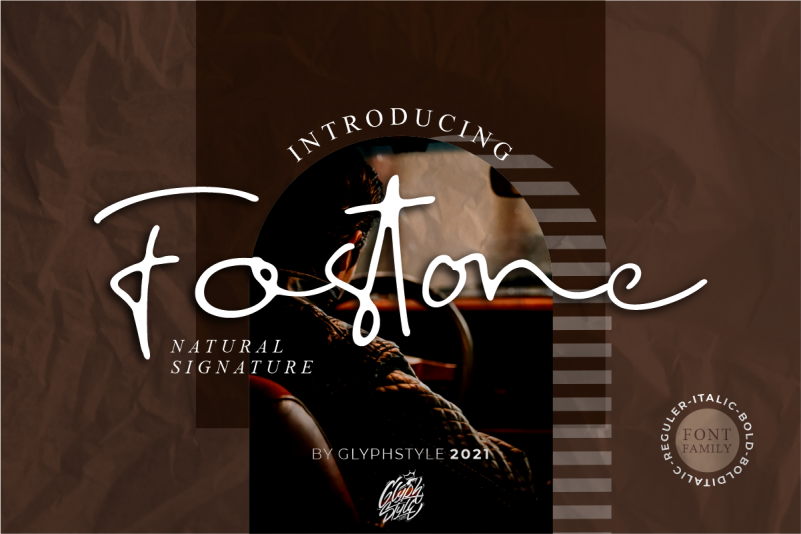
Fostone Natural Signature Script Font – Download Grátis
A Fostone Natural Signature Script Font é uma escolha perfeita para quem busca um estilo elegante e sofisticado que lembra o traço delicado de um papel hidrografia antiga. Seu charme natural, reminiscente de um caderno de bilhetes feito com uma caneta a ponta de ouro, é tão luxuoso quanto sedutor. Este font foi projetado para capturar aquele brilho único que o mundo dos negócios adora — seja através da criação de logotipos de marca, cartões de visita, logos de produtos ou até mesmo como um elemento de destaque em trabalhos de marca digital. Com quatro versões (regular, bold, italic e bolditalic), a Fostone Natural Signature Script Font é uma ferramenta versátil que pode ser usada em diversos contextos. Ela oferece o aspecto perfeito para aquelas criações onde um toque autêntico e elegante conta muito mais do que nunca antes. Esta font não apenas se encaixa confortavelmente no universo da escrita digital, mas também adiciona um toque de sofisticação à qualquer projeto visual, tornando-a uma opção ótima para profissionais buscando elementos diferenciadores em seus trabalhos.